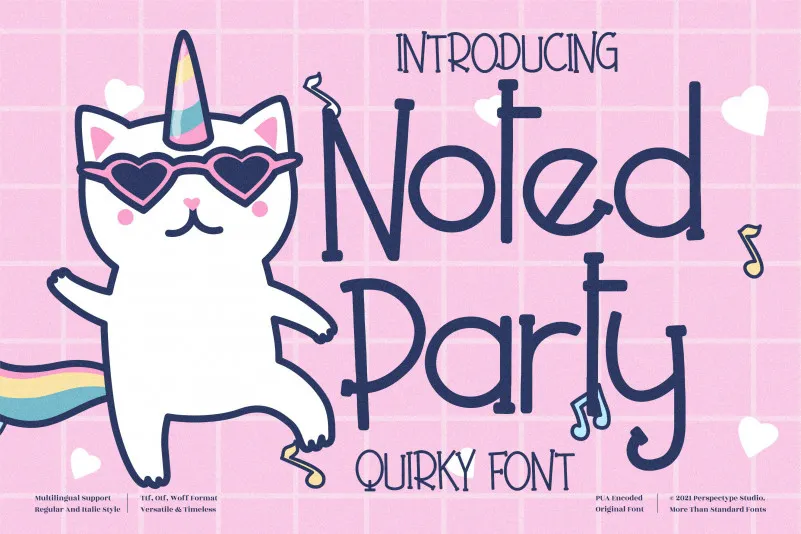
A Noted Party Font é uma fonte casual e alegre ideal para quem procura algo que se destaque em sua biblioteca de fonts. Com seu tema descontraído, este recurso vem desenhado para encantar qualquer tarefa ou projeto. Seja para criar um cartão de aniversário divertido, designar uma identidade visual agradável para sua marca pessoal ou simplesmente decorar um documento com estilo, esta fonte é definitivamente uma ferramenta valiosa e inovadora. Proposta para designers em busca de algo que brinque com as nuances da tipografia sem comprometer o trabalho final, Noted Party Font atua como um acessório agradável e divertido. Suas linhas leves e suas formas suaves criam uma sensação de relaxamento, permitindo que qualquer projeto assuma um tom mais descontraído e animado. Não importa qual seja seu propósito com essa fonte, ela certamente pode fazer do seu trabalho algo único, destacando sua personalidade para o mundo. Seja você um designer gráfico ou criador de conteúdo digital, a Noted Party Font é uma escolha a ser considerada ao procurar por uma fonte casual e divertida que não apenas atende aos seus requisitos, mas também eleva cada projeto à próxima dimensão.